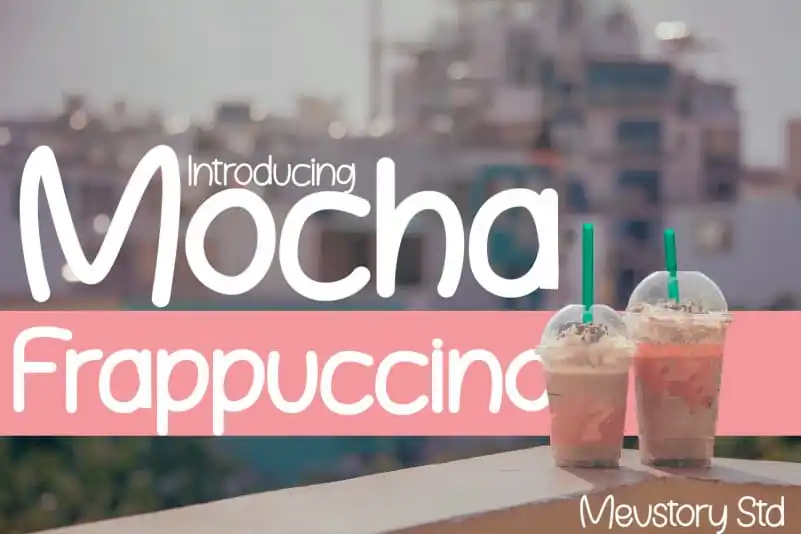
Mocha Frappuccino Free Font – Download Grátis
A fonte ‘Mocha Frappuccino Free Font’, do tipo Display Font criada pelo designer mhdafifersya, é uma combinação única e vibrante que transmite uma sensação de alegria sem deixar de manter um padrão sóbrio. Inspirada no famoso refrigerante Mocha Frappuccino da Starbucks, essa fonte possui muitos caracteres inter-relacionados, o que dá à sua usabilidade um caráter divertido e único. O designer inclui uma característica chamada “Naughty Monster”, presente somente em versão OpenType, que permite que cada caractere seja transformado em ligaturas. Isso não apenas torna a fonte mais personalizável e interessante para designers, mas também adiciona um toque inusitado e divertido à aparência final de qualquer projeto. Tal característica é particularmente útil em projetos variados, desde a criação de logotipos ou adesivos até o design das capas de livros. A fonte mantém uma estrutura elegante e formal ao mesmo tempo que oferece um toque desconcertantemente alegre, tornando-a extremamente versátil para qualquer aplicação de design. Seja em projetos de mídia social ou em campanhas publicitárias, ‘Mocha Frappuccino Free Font’ trará um toque divertido e criativo à sua identidade visual.